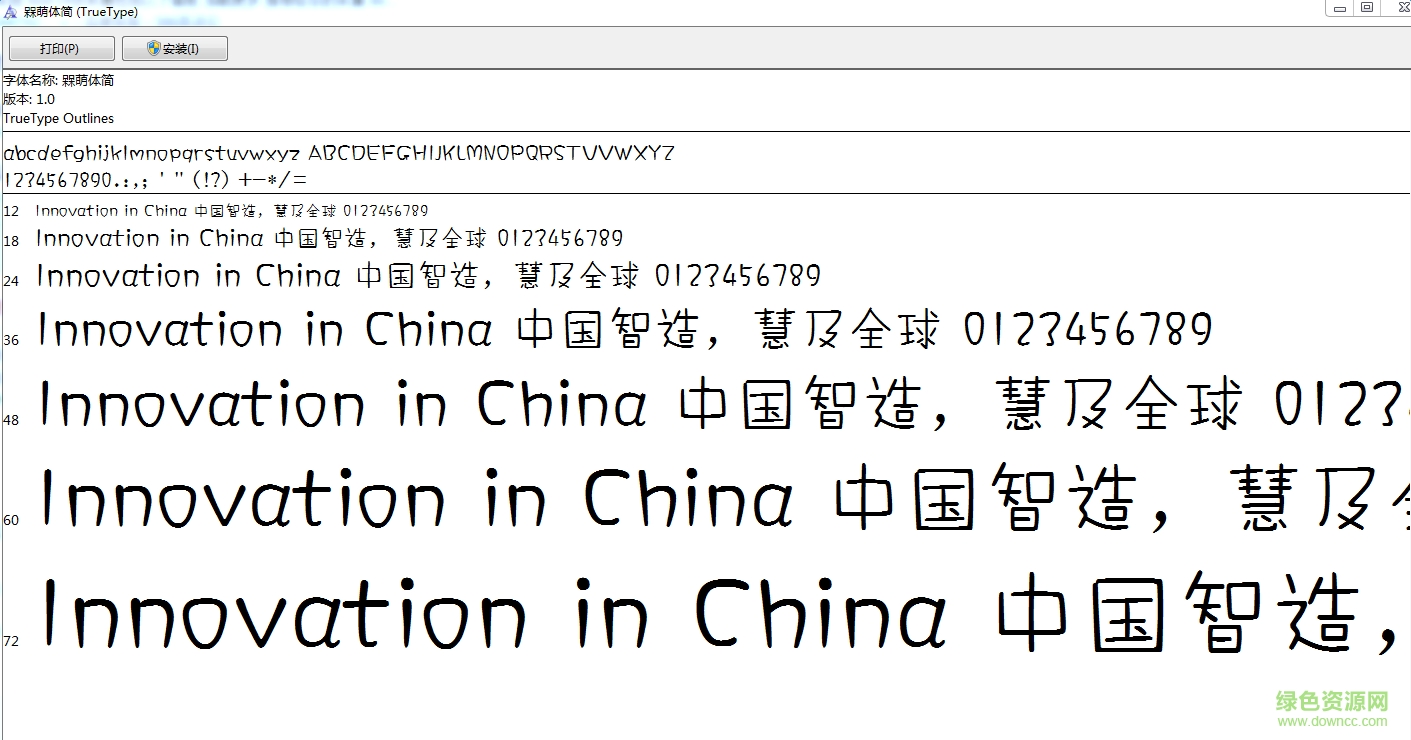
漢儀槑萌體
儀呆萌體又稱儀槑萌體簡體,是一款ttf格式的手寫版簡體字體,字體可愛清新,廣告設計、兒童海報、ppt等都可使用該款字體,喜歡的小伙伴歡迎在綠色資源網(wǎng)下載收藏!
漢儀呆萌體介紹
漢儀呆萌體是一款兒童手寫風格的藝術字體,字體筆畫帶有稚氣,活潑可愛,非常具有趣味性。整體效果十分出色。喜歡的朋友趕快下載吧。